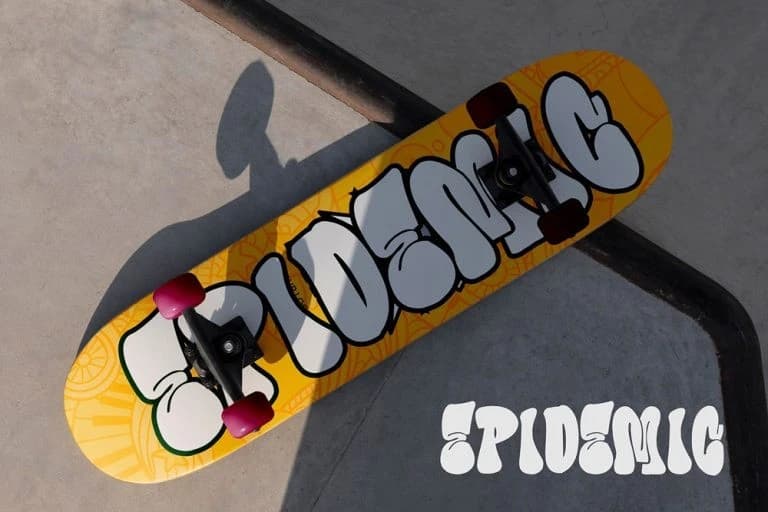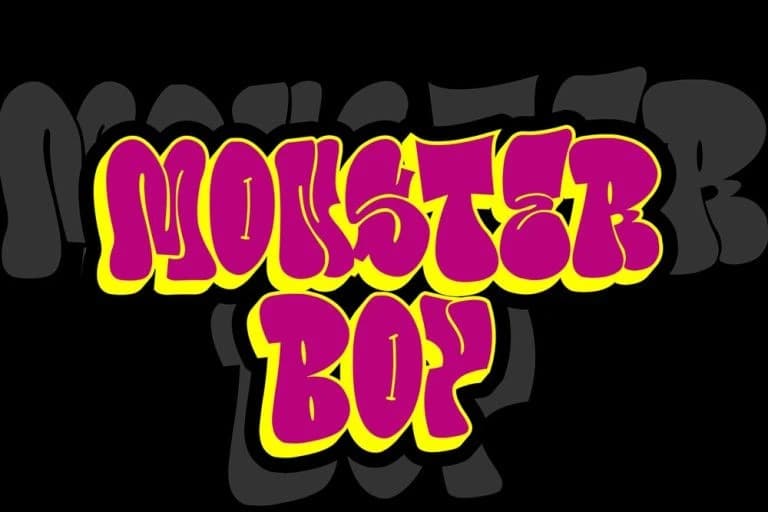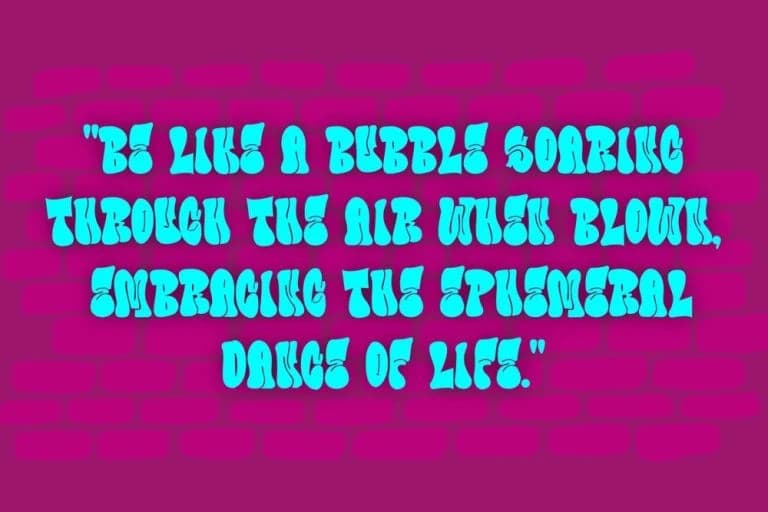
Bubble Horns Yazı Tipi
Bubble Horns Font, otantik throw-up sokak yazılarına ilham veren cesur ve eğlenceli bir grafiti yazı tipidir. Yuvarlak kabarcık şekiller ve enerjik bir kentsel akışla tasarlanan bu throw-up grafiti yazı tipi, grafiti kültürünün hızlı tempolu ruhunu yakalarken eğlenceli ve okunması kolay bir tasarım
Bubble Horns Font, otantik throw-up sokak yazılarından ilham alan cesur ve oyuncu bir grafiti fontudur. Yuvarlak kabarık şekiller ve enerjik kentsel akış ile tasarlanmış olan bu throw-up grafiti fontu, grafiti kültürünün hızlı temposunu yakalar ve aynı zamanda eğlenceli ve son derece okunabilir bir tasarım sunar.
Bubble Horns